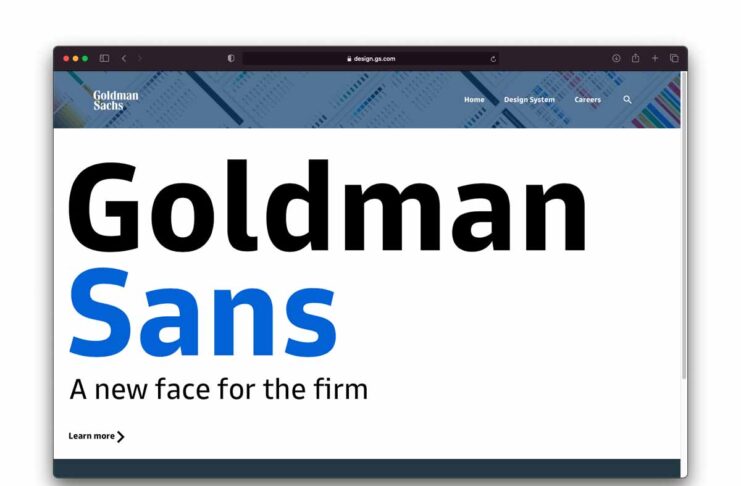
La grande banca di affari Goldman Sachs ha presentato un suo font, un carattere sans-serif (senza grazie) denominato “Goldman Sans”. Il sito BoingBoing fa notare una curiosa condizione indicata per l’utilizzo del font: nella licenza d’uso è espressamente indicato che è possibile utilizzarlo liberamente purché non sia usato per criticare Goldman Sachs.